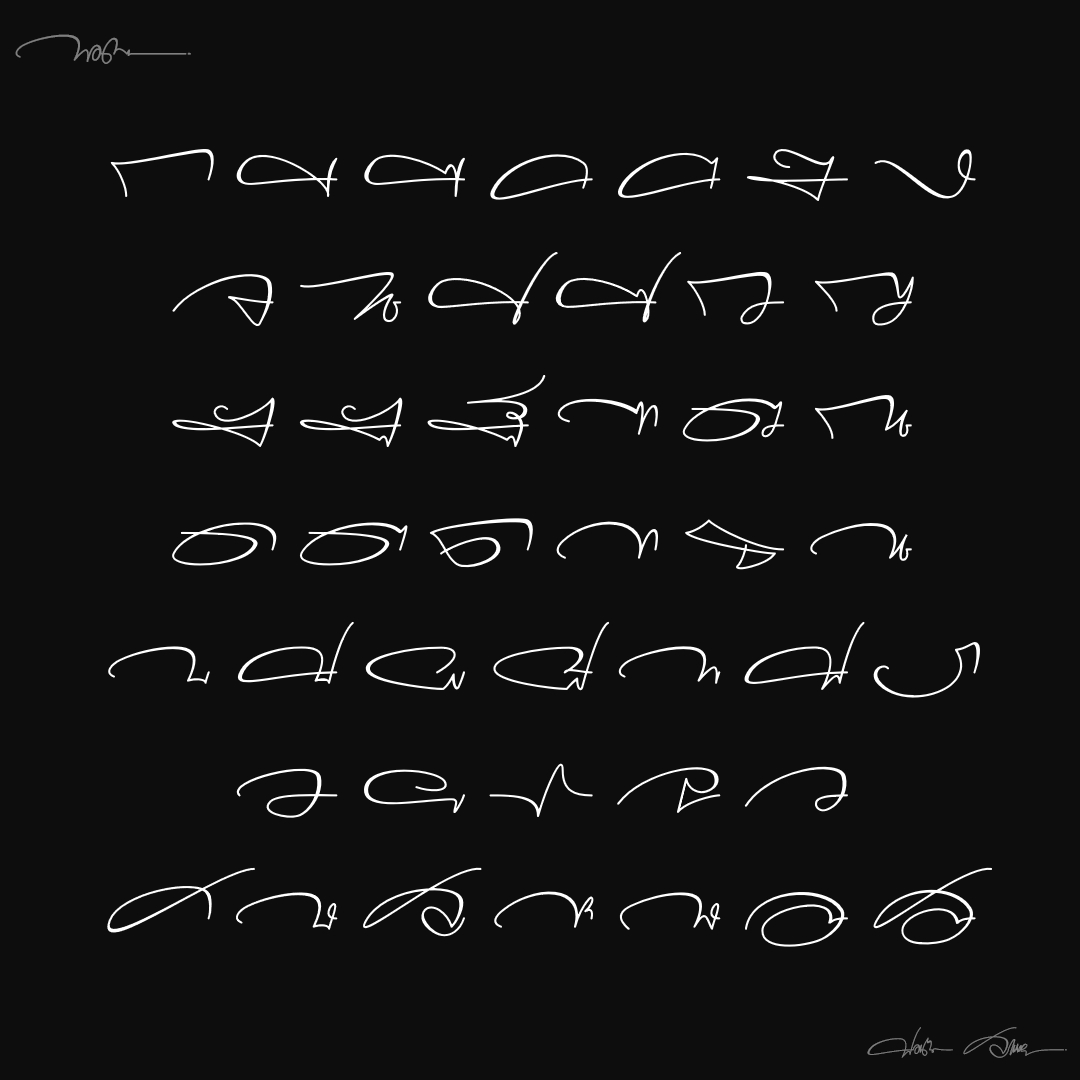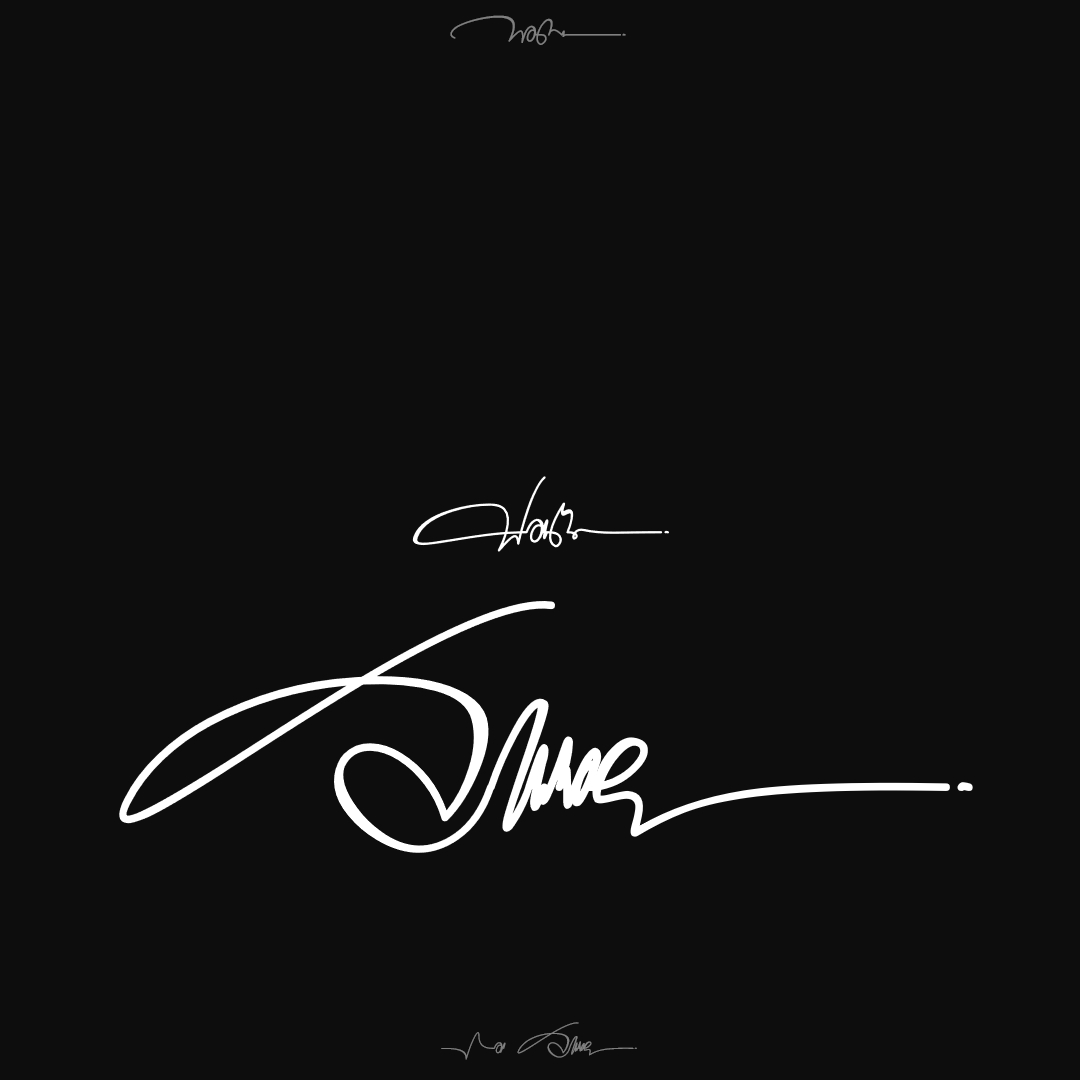
ฟอนต์ ๓๐๐
ฟอนต์แนวลายเซ็น ที่ไม่ยึดหลักมงคลส่งเสริมโชคลาภใดๆ อย่าเอาไปใช้หลอกลวงใครนะจ๊ะ
ใช้ได้ทั้ง คำเดียว และแบบชื่อ นามสกุล
ตัวอักษรเดียวไม่ได้ตวัดหาง
ใช้กับแพนแกรม หรือประโยค
ชื่อฟอนต์ : 300
ฟอนต์แนวลายเซ็น ที่ไม่ยึดหลักมงคลส่งเสริมโชคลาภใดๆ อย่าเอาไปใช้หลอกลวงใครนะจ๊ะ